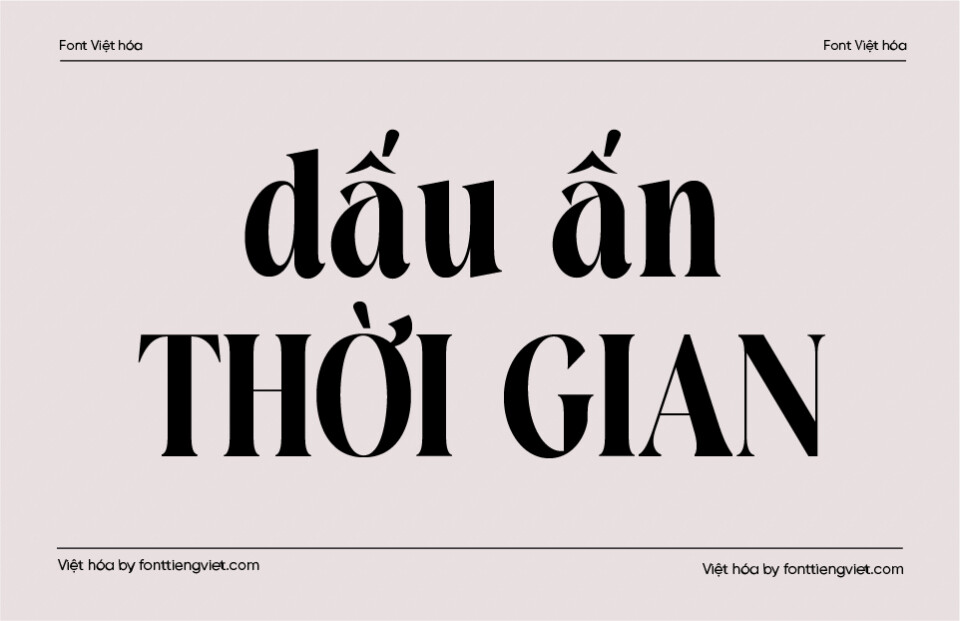
Tải Font Việt hóa 1FTV VIP Arkosic Miễn Phí Cho Thiết Kế Chuyên NghiệpGiới thiệu về bộ Font Việt hóa 1FTV VIP ArkosicTrong thế giới đồ họa hiện đại, việc lựa chọn một bộ Font Miễn Phí chất lượng luôn là ưu tiên hàng đầu của các nhà thiết kế. Font Việt hóa 1FTV VIP Arkosic nổi lên như một hiện tượng nhờ sự kết hợp hoàn hảo giữa nét cổ điển và hơi thở đương đại. Đây là một phông chữ thuộc phong cách Serif với các đường nét tinh tế, chân chữ sắc sảo và tỷ lệ cân đối, tạo nên một cảm giác sang trọng nhưng không kém phần gần gũi. Việc sử dụng Font Việt hóa 1FTV VIP Arkosic trong các dự án học đường hay trang trí báo tường sẽ giúp nội dung trở nên thu hút và có điểm nhấn hơn hẳn so với các phông chữ truyền thống thông thường.Đặc điểm nổi bật của Font Việt hóa 1FTV VIP ArkosicĐiểm mạnh nhất của Font Việt hóa 1FTV VIP Arkosic chính là khả năng hiển thị tiếng Việt trọn vẹn. Các dấu câu được thiết kế tỉ mỉ, không bị lỗi font hay nhảy chữ khi gõ văn bản dài. Điều này cực kỳ quan trọng đối với học sinh và giáo viên khi cần soạn thảo tài liệu hoặc trình chiếu bài giảng. Ngoài ra, bộ font này còn có nhiều biến thể từ nét mảnh đến nét đậm, cho phép người dùng linh hoạt trong việc tạo tiêu đề nổi bật hay trình bày nội dung chi tiết một cách mạch lạc. Sự đa dạng này giúp Arkosic trở thành công cụ đắc lực cho mọi ý tưởng sáng tạo từ đơn giản đến phức tạp.Ứng dụng thực tế của Font Việt hóa 1FTV VIP Arkosic trong học tậpĐối với môi trường giáo dục, Font Việt hóa 1FTV VIP Arkosic mang lại sự chuyên nghiệp cho các bài thuyết trình PowerPoint. Khi các em học sinh sử dụng phông chữ này, bài làm sẽ trông bắt mắt và dễ theo dõi hơn, từ đó nâng cao hiệu quả truyền tải kiến thức. Không chỉ dừng lại ở đó, các thầy cô giáo cũng có thể dùng Arkosic để thiết kế các mẫu phiếu bài tập hoặc thư mời họp phụ huynh, tạo ấn tượng tốt về sự chỉn chu và tận tâm. Khả năng đọc hiểu tốt của phông chữ này giúp giảm mỏi mắt khi phải làm việc với văn bản trong thời gian dài trên màn hình máy tính.Cách kết hợp Font Việt hóa 1FTV VIP Arkosic với các font khácĐể tạo nên một bản thiết kế hoàn hảo, bạn nên kết hợp Font Việt hóa 1FTV VIP Arkosic với các phông chữ không chân (Sans Serif) tối giản như Montserrat hoặc Roboto. Sự tương phản giữa chân chữ điệu đà của Arkosic và sự hiện đại của các font không chân sẽ tạo nên một bố cục hài hòa, đẳng cấp. Bạn có thể sử dụng Arkosic cho các tiêu đề lớn và dùng font không chân cho phần nội dung mô tả để đảm bảo tính thẩm mỹ cao nhất.Lưu ý và hướng dẫn cài đặt Font Việt hóa 1FTV VIP ArkosicViệc cài đặt Font Việt hóa 1FTV VIP Arkosic vô cùng đơn giản trên cả Windows và macOS. Sau khi tải về, bạn chỉ cần giải nén tệp tin, chuột phải vào các định dạng .otf hoặc .ttf và chọn Install. Ngay lập tức, phông chữ sẽ xuất hiện trong các phần mềm quen thuộc như Word, Photoshop hay Canva. Tuy nhiên, người dùng cần lưu ý chỉ nên sử dụng bộ font này cho các mục đích cá nhân và học tập để tôn trọng bản quyền của tác giả thiết kế gốc.Kết luận về bộ Font Việt hóa 1FTV VIP ArkosicTóm lại, Font Việt hóa 1FTV VIP Arkosic là một lựa chọn không thể bỏ qua cho bất kỳ ai đang tìm kiếm sự mới mẻ và chuyên nghiệp trong trình bày văn bản. Với đầy đủ bộ dấu tiếng Việt và tính thẩm mỹ vượt trội, phông chữ này chắc chắn sẽ làm hài lòng ngay cả những người dùng khó tính nhất. Hãy truy cập ngay Font Miễn Phí, Font Việt Hóa, Font Việt hóa 1FTV VIP Arkosic để tải về và trải nghiệm sức sáng tạo không giới hạn mà bộ font này mang lại cho dự án của bạn.
Font Việt hóa 1FTV VIP Arkosic